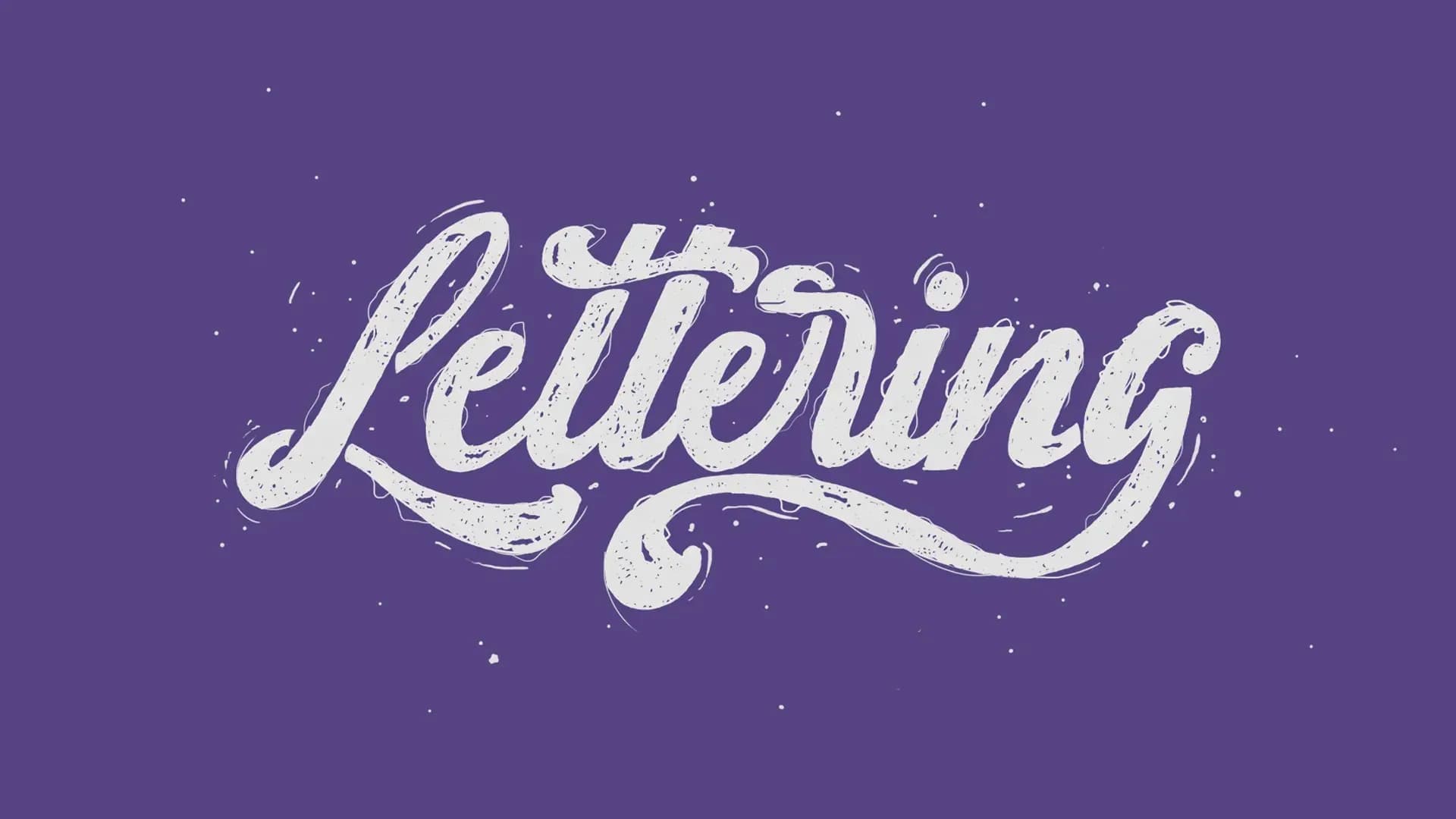
¿Saben cuáles son las diferencias entre el lettering, caligrafía y tipografía? Cuando se habla de lettering, caligrafía o tipografía es normal toparnos con un debate sobre quien es quien. Los tres conceptos hacen alusión a las letras, aunque es lo único que tienen en común.
Para quienes no están familiarizados a profundidad con el tema es normal que existan dudas sobre estos conceptos. En este primer artículo del año, y de nuestro tema del mes, veremos las diferencias despejando las dudas que existan. Estos conceptos son menos confusos de lo que aparentan.
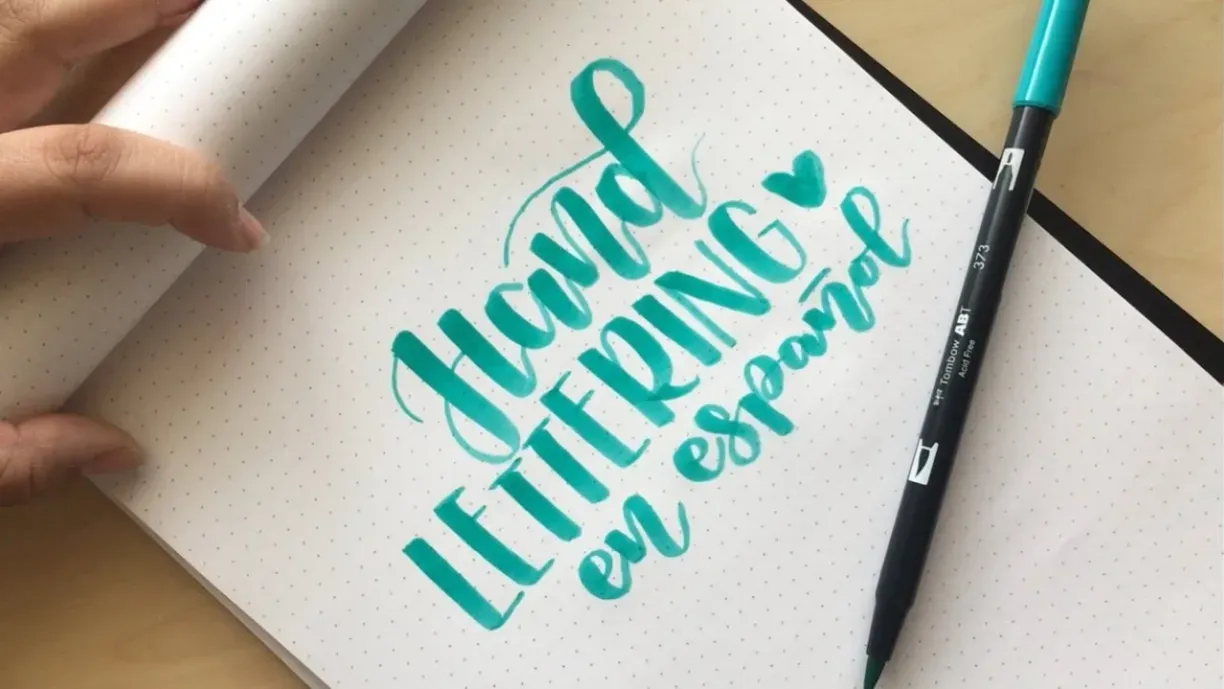
El lettering consiste en dibujar letras, palabras o frases. A diferencia de la caligrafía donde se escriben más no dibujan. Este hecho implica que uno puede corregir un mal trazo o rehacer todo desde cero. En el lettering las letras pueden generarse de forma analógica o a partir de vectores. También se pueden realizar con otros métodos digitales, por lo que, las letras no deben ser necesariamente únicas. ¿Qué significa esto? Que pueden copiarse entre sí, dando de esta forma un aspecto más uniforme.
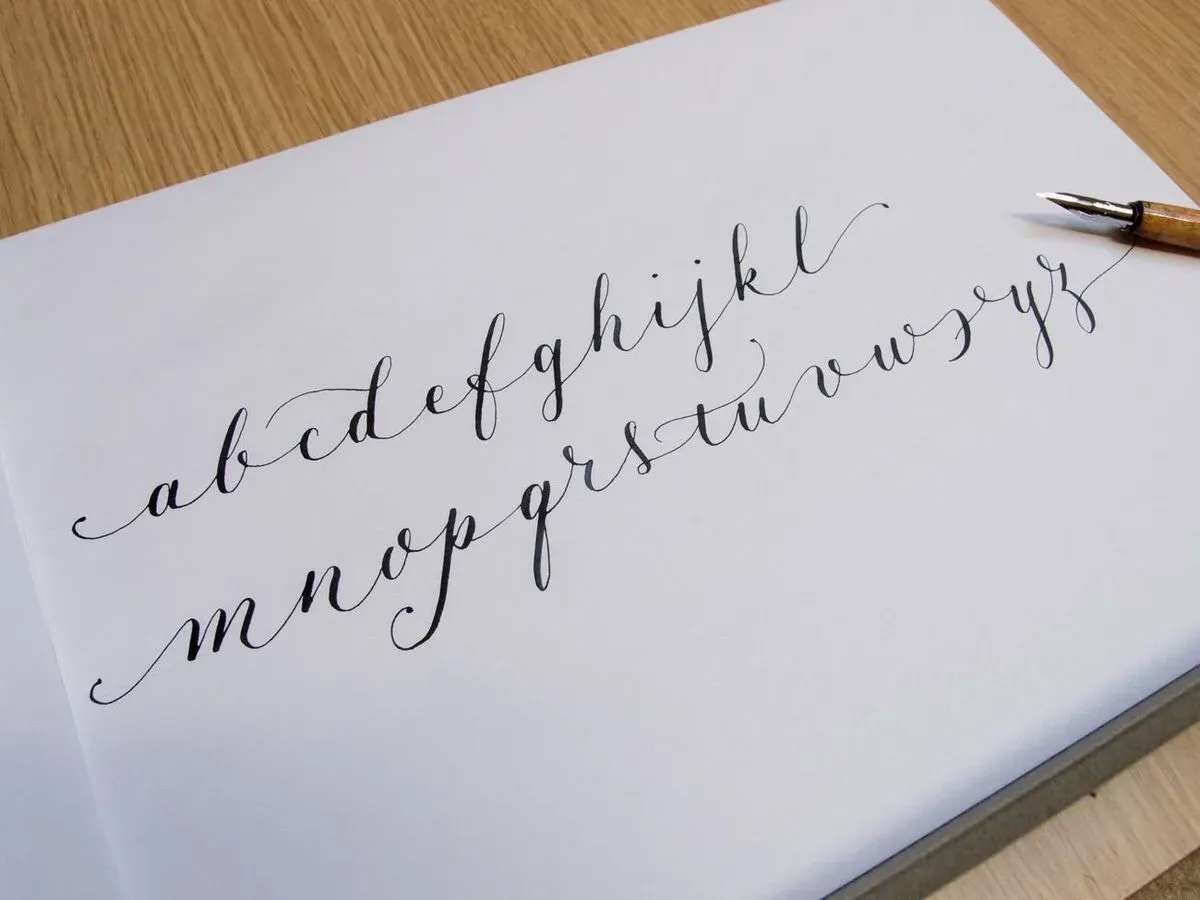
A diferencia del lettering, consiste en la escritura de letras prestando atención al modo, la dirección, secuencia y velocidad de los trazos. Otra diferencia es su realización, ya que debe ser sí o sí, a mano. Dado a que se realiza a mano, se deben utilizar herramientas especiales para dicha tarea. Entre estas herramientas están las plumas, rotuladores, pinceles entre otros. Actualmente también puede realizarse de forma digital por medio de una tableta; siempre y cuando sea de forma manuscrita.
Algo a tener en cuenta, es que en la caligrafía las partes significativas de cada letra deben ser delineadas en un solo trazo. No admite correcciones en los malos trazos ni en partes. Hay diferentes técnicas de escritura que se pueden aprender para este fin.
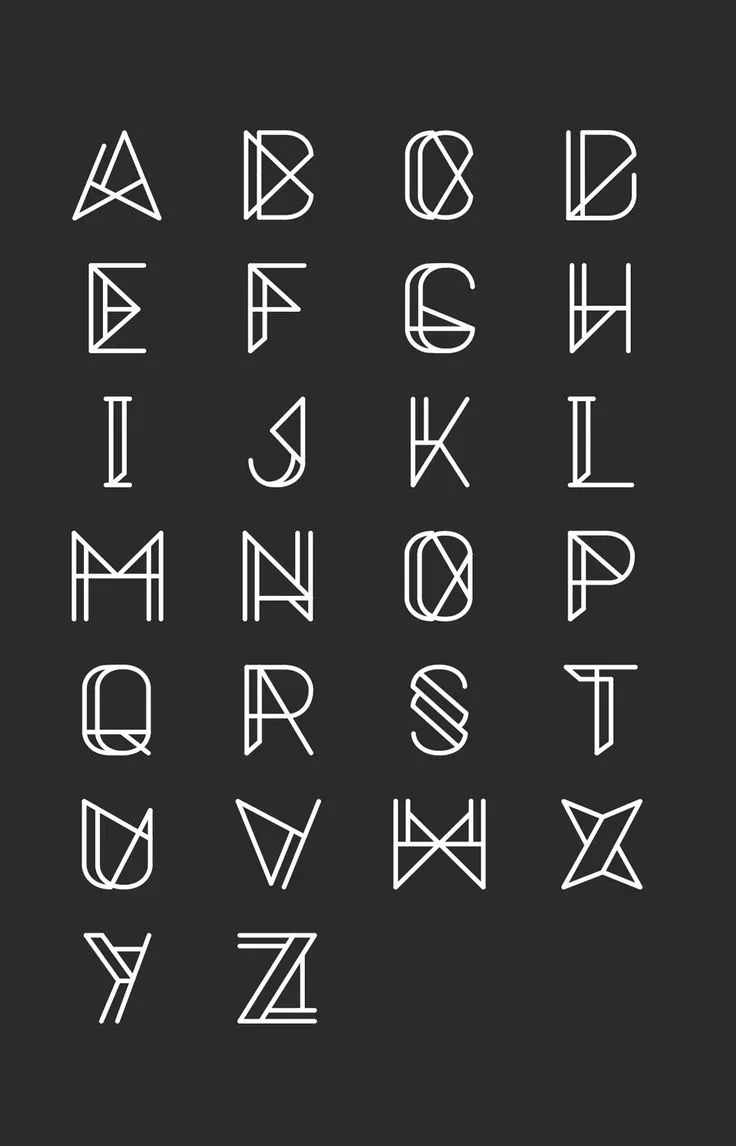
Las tipografías suelen ser creadas por diseñadores, los cuales no crean letras ni glifos únicos como los calígrafos ni las dibujan como los letristas. Una tipografía no es más que un conjunto único de caracteres que comparten una estética y unidad entre sí.
Por lo general, el diseñador de tipografías diseña las letras, números y demás signos los cuales eventualmente deberá programar. En dicha programación se establecen los parámetros esenciales que se repetirán sistemáticamente en dicho conjunto de caracteres. En resumen, el lettering es dibujar letras, palabras o frases, la caligrafía es escribir de forma agradable a la vista letras y la tipografía es un conjunto de caracteres que comparten una unidad estilística.